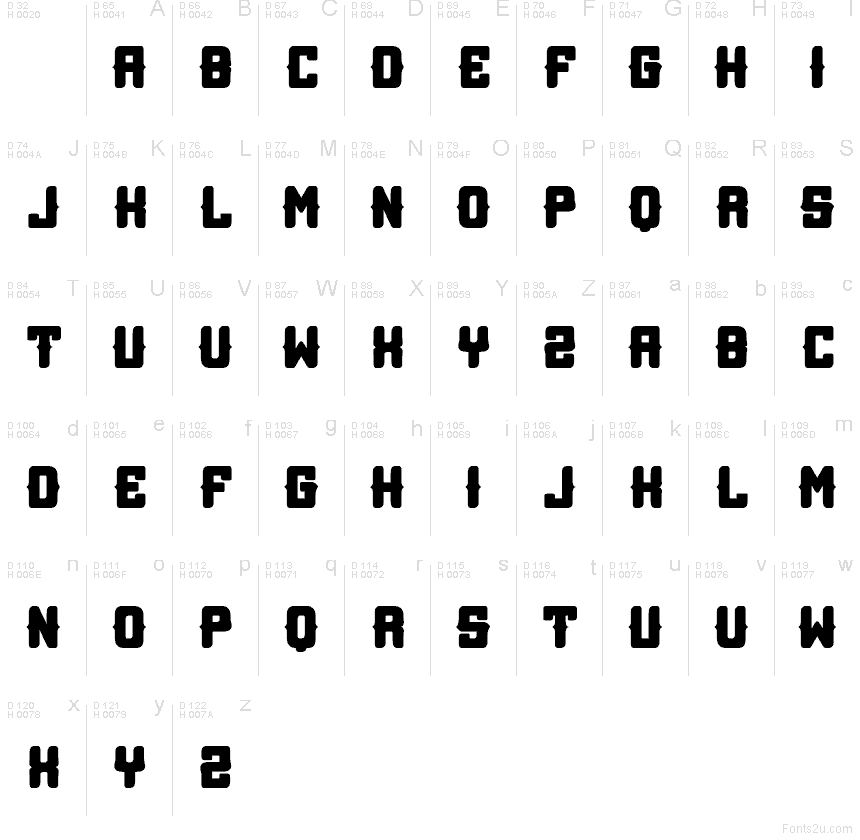
Sombrero Pintado di Vladimir Nikolic è un carattere display gratuito in stile messicano, caratterizzato da maiuscole ampie e corpose, un baricentro basso e un'aria festosa da manifesto. Gli angoli marcatamente arrotondati ammorbidiscono silhouette dense, mentre netti intagli verso l'interno donano alle aste un profilo rastremato distintivo lungo i lati. Piccole aperture squadrate e archi esagerati aggiungono varietà a glifi compatti e ravvicinati.
Funziona in modo convincente come insegna da cantina dipinta a mano. Questo ruolo si addice al branding di ristoranti, a etichette alimentari, poster per festival e merchandising musicale, dove gli intagli ricorrenti e le curve bombate possono richiamare le cornici geometriche e le illustrazioni in carta ritagliata tipiche della grafica festosa messicana.